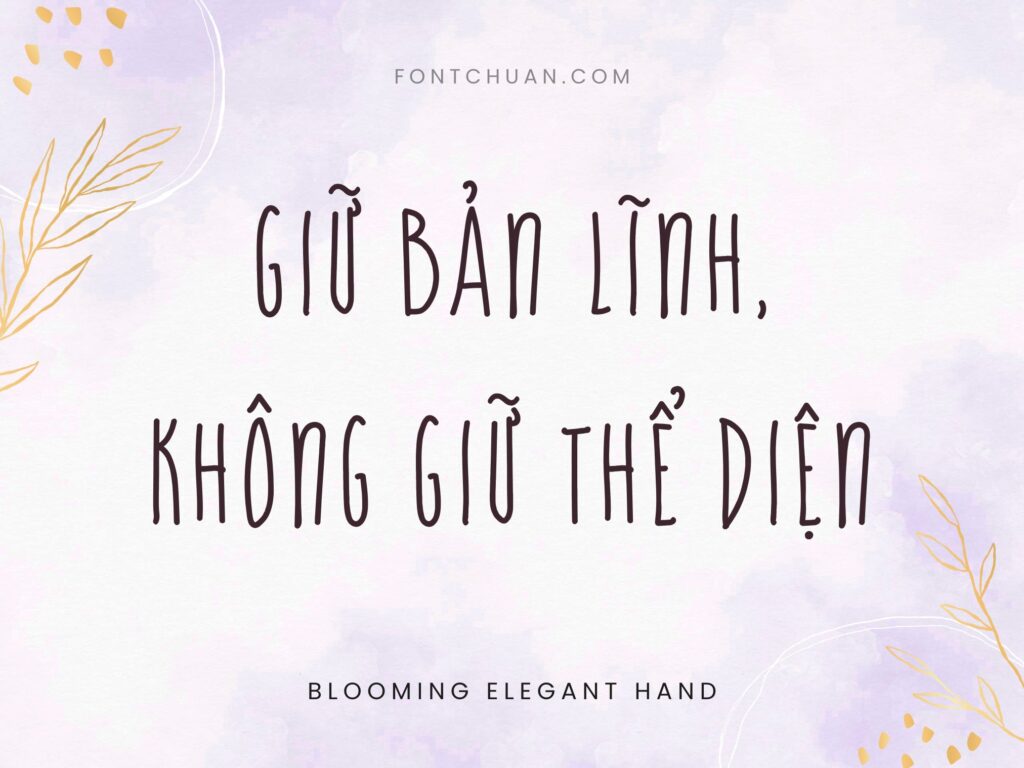
Font iCiel Blooming Elegant Trọn Bộ Việt Hóa
Tác giả Font: Nicky Laatz
Việt hóa bởi: Iciel
Blooming Elegant là một bộ ba font chữ thanh lịch và tinh tế, được thiết kế bởi Nicky Laatz. Bộ font này bao gồm Blooming Elegant Regular, Blooming Elegant Sans và Blooming Elegant Hand, mang đến sự đa dạng và linh hoạt cho các dự án thiết kế. Để hỗ trợ cộng đồng thiết kế Việt Nam, Iciel đã Việt hóa bộ font Blooming Elegant, giúp bộ font này hỗ trợ đầy đủ tiếng Việt cùng hơn 200 ngôn ngữ khác. Phiên bản Blooming Elegant Việt hóa đã được thành viên Font Chuẩn sưu tầm và đăng tải, mang đến sự lựa chọn phong phú cho các nhà thiết kế.
Về đặc điểm thiết kế, Blooming Elegant Regular là một font script với đường nét uyển chuyển và duyên dáng, phù hợp cho các thiết kế như thiệp mời, logo, tiêu đề và bao bì sản phẩm. Blooming Elegant Sans là một font sans-serif đơn giản và hiện đại, hoàn hảo cho văn bản nội dung và tiêu đề phụ. Blooming Elegant Hand mang phong cách viết tay tự nhiên, thêm phần cá tính và ấm áp cho các dự án thiết kế. Bộ ba font này rất phù hợp cho các ngành nghề như quảng cáo, thiệp cưới, ẩm thực và giáo dục, mang lại phong cách chuyên nghiệp và thu hút. Ngoài ra, bộ font cũng thích hợp để sử dụng trong các sự kiện như Valentine, Sinh nhật và các dịp lễ hội.